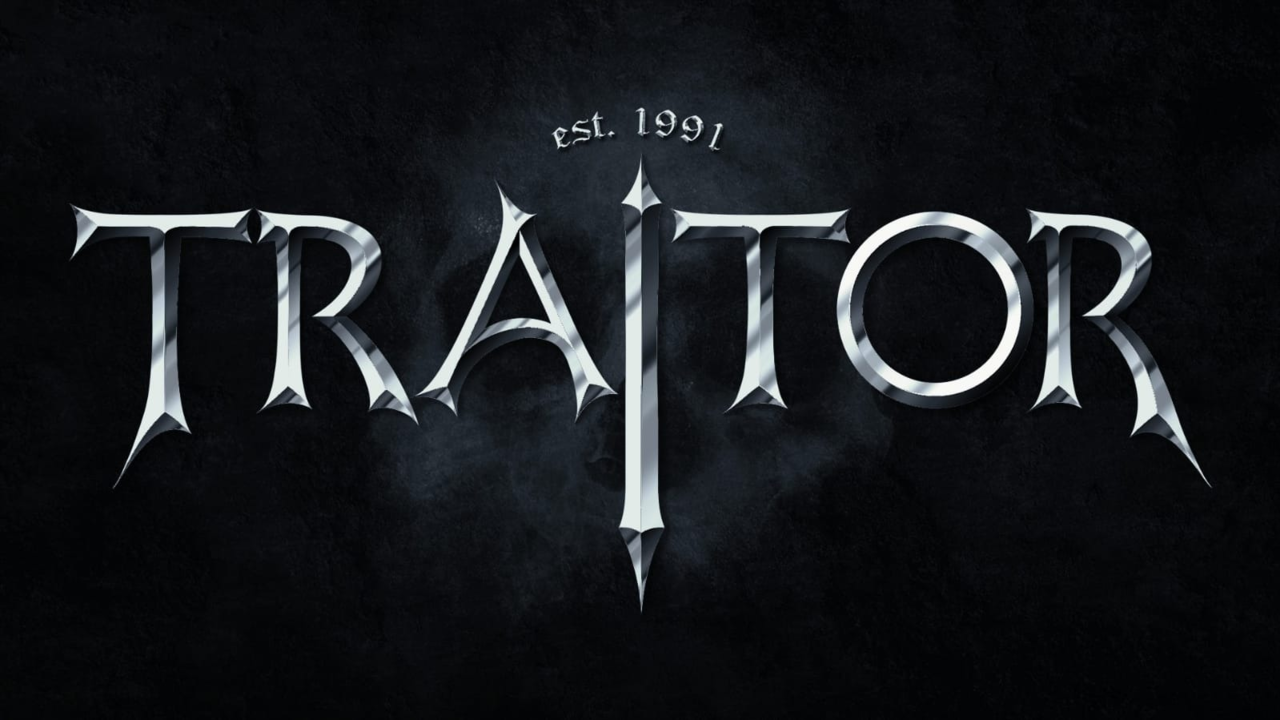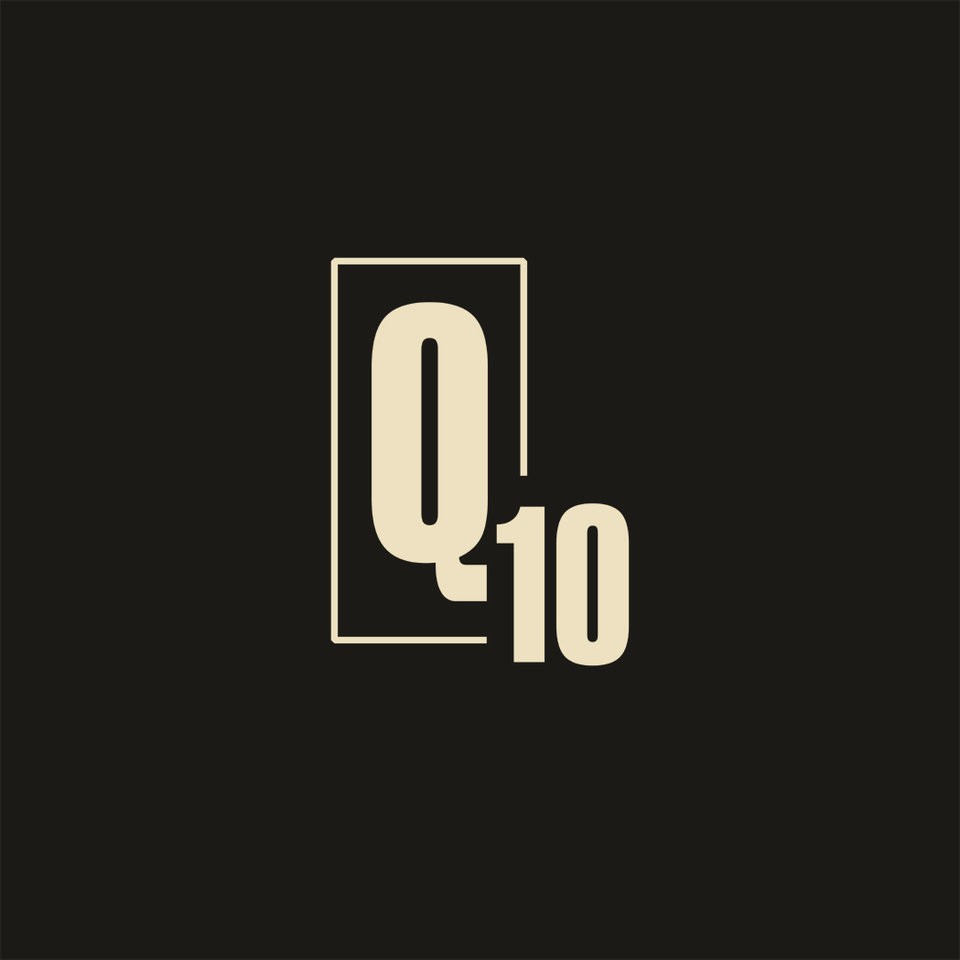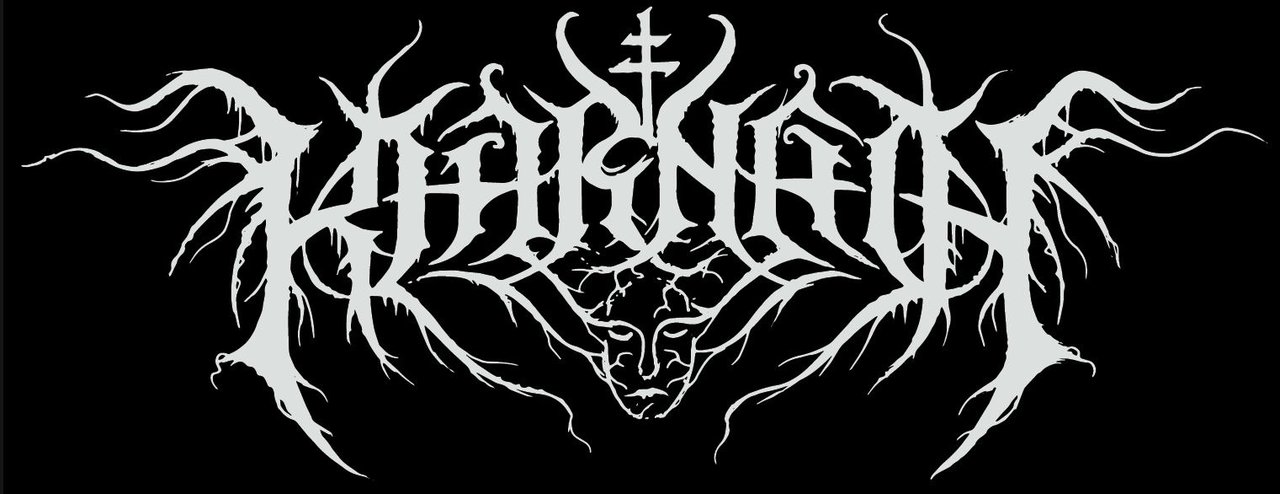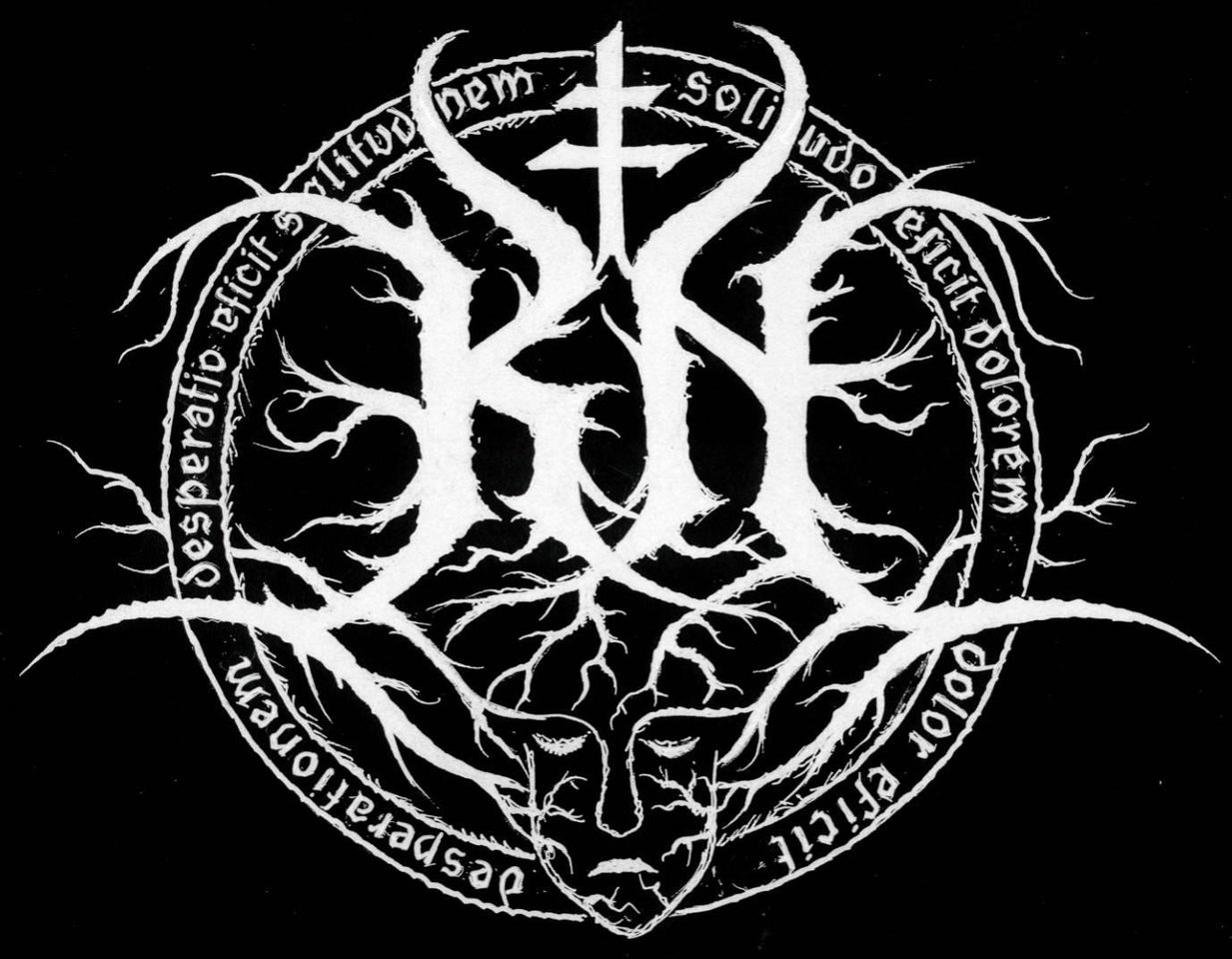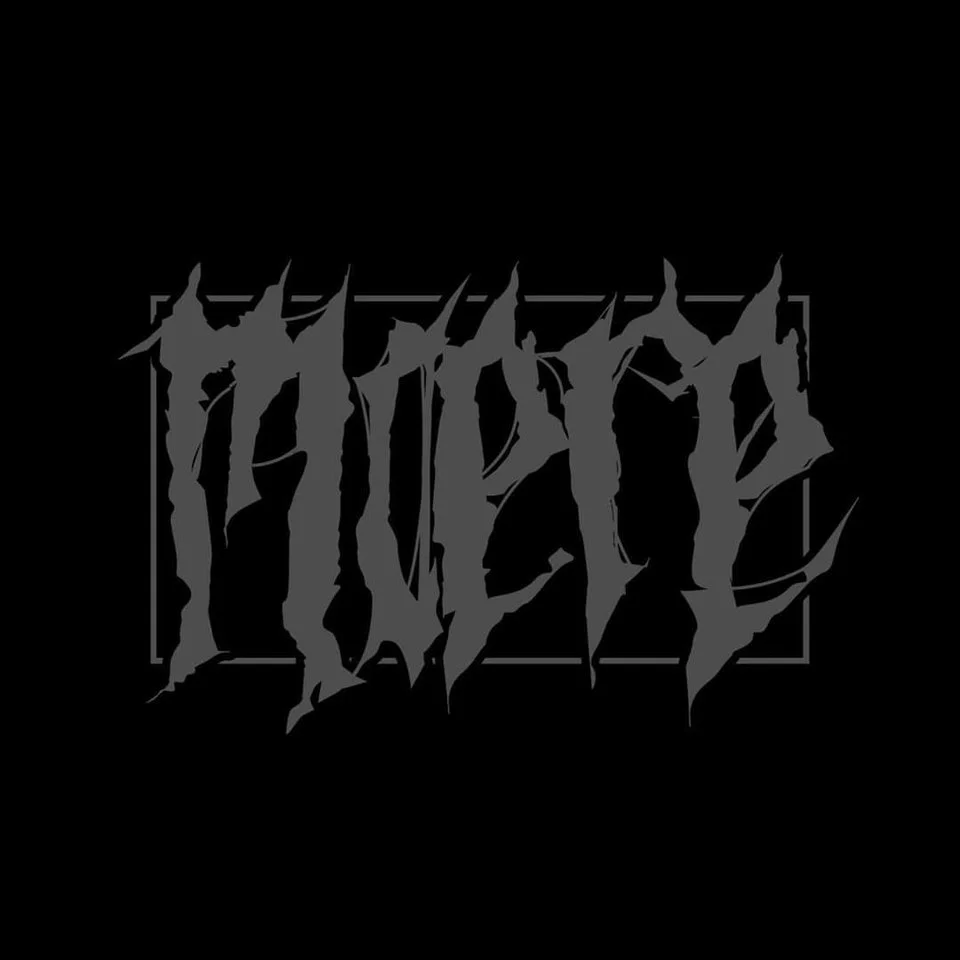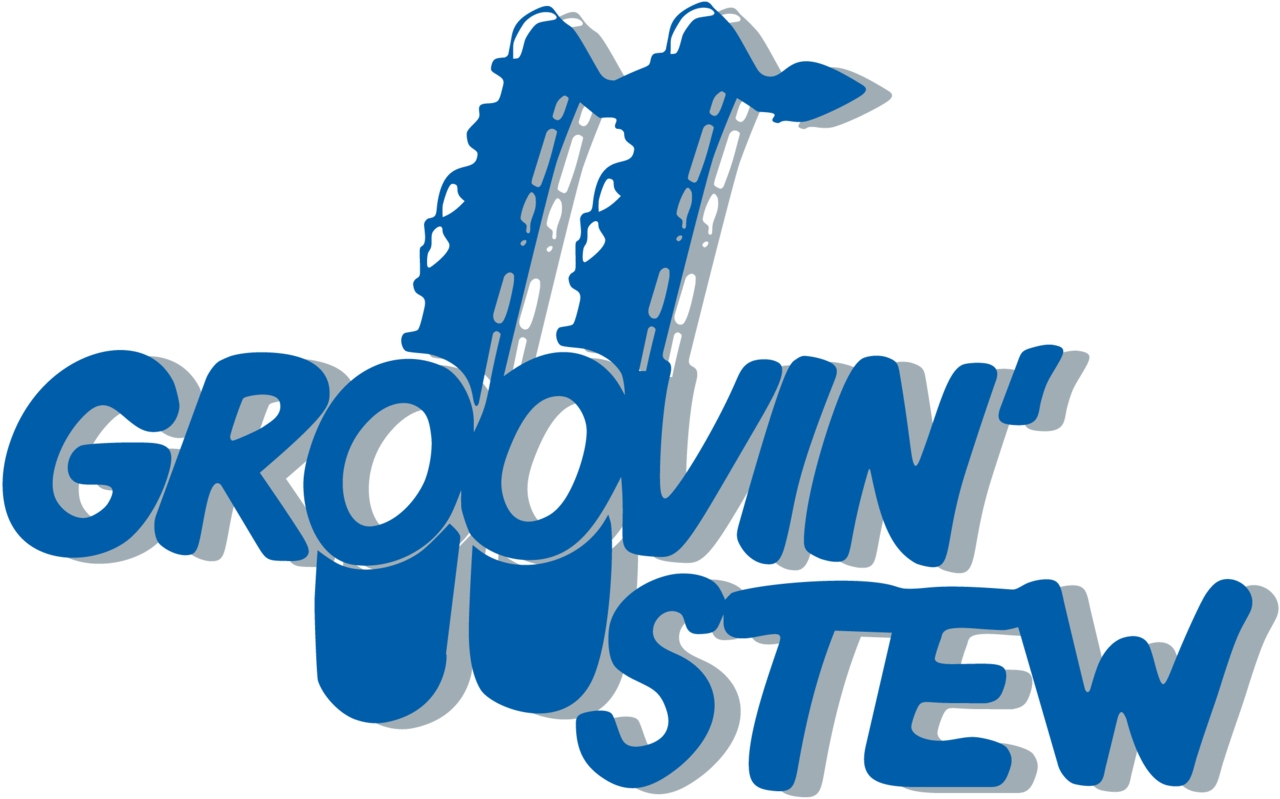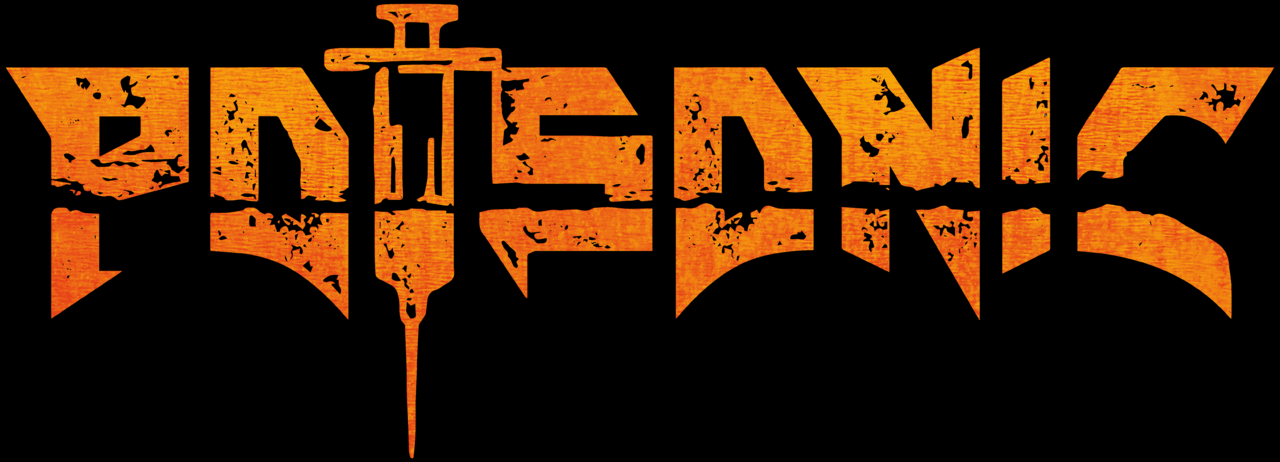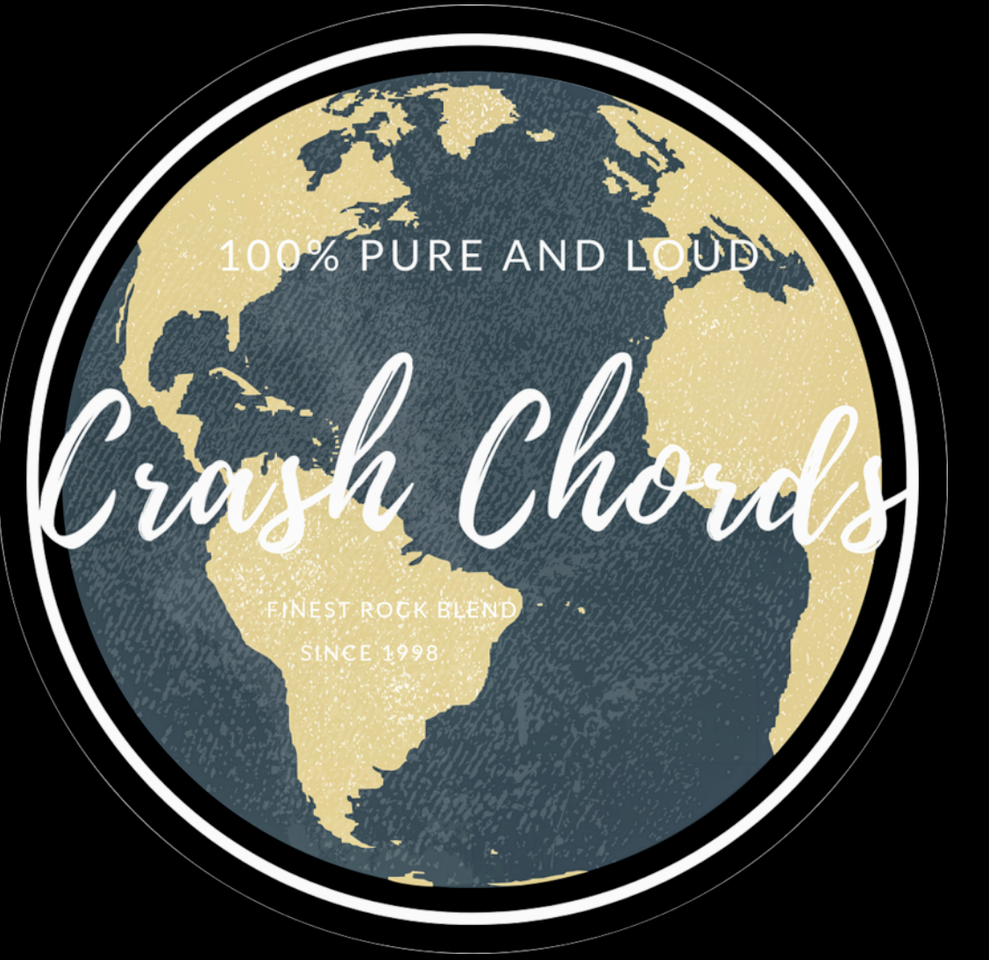
Euer Bandlogo-Artwork-Schriftart... her damit...!
Bei uns war der Name (Kharnath) eigentlich sofort gefunden, unseren Logodesigner (Christophe Szpajdel - unter anderem Verantortlich für Logos von Band wie Dark Fortress, Emperor, Moonspell, Nargaroth, Wolves In The Throneroom, Abigail Williams oder auch das aktuelle von Rhiana) haben wir einfach per Mail kontaktiert und angefragt und schon ging das ganze sehr flott und unkompliziert für das Logo und Bandsymbol von statten. Besonders gefallen hat uns dabei immer wieder, dass er Rücksprache mit uns gehalten hat und auch auf unsere Ideen udn Wünsche eingegegangen ist. Und natürlich dass der gute Herr noch alles per Hand zeichnet. UNd als Bonus ist er auch noch seeeeehr günstig gewesen, was uns aufgrund seines doch recht großen bekanntheitsgrades schwer verwundert hat. Und ein netter kerl noch dazu (schön zu sehen wie der Designer sich über ein Shirt mit seinem Logo freut, wenn man ihn zufällig auf nem Festival trifft).
Zu Herkunft des Namens und des Logos muß ich unseren Sänger in seiner Eigenschaft als einzig verbleibendes Gründungsmitglied befragen. Ich bin ja erst seit Anfang diesen Jahres dabei.
Edit möchte ergänzen, daß das auf schwarzem Hintergrund besser aussieht. In der Grafikdatei war der aber offenbar nicht mit drin...
Edit2: Interessanterweise hat man schwarzen Hintergrund, wenn man die Grafik anklickt. Kann man das beim Einbinden auch einstellen?
Der Hintergrund ist transparent, deshalb direkt im Thread so wie dargestellt. Das Plugin hier beim Anklicken hat standardmäßig den schwarzen Hintergrund, der dann logischerweise auch hinter der Transparenz gezeigt wird. Windoofs Bild-Anzeige interpretiert gefühlt je nach Laune Transparenz zu schwarz oder zu diesem Blassgrau ausm Explorer.
das hier is das logo meiner ex-band, gestaltet von einer befreundeten grafikerin. sehr schön schlicht, reduziert, finde ich bis heute super.
für die aktuelle band sind wir noch auf der suche nach einem schönen design. spätestens, wenn der mix der aufnahmen fertig ist, brauchen wir was für's tapecover ...
Mein Gehirnblitz in Krankheit bei Fall vom Dach. Alles fanden es gut und so war es geboren.
Steht ja in ähnlicher Art in vielen Straßen :rolleyes:
Tadaaa
Moere? Aber nein, das schreibt man ja mit "h". :gruebel:
Hier haste's orange auf schwarz als Bilddatei:
(Sieht ja auch wirklich besser aus.)
Zur Gestaltung:
Das ist auch Metall-Stil. Kann man aber gut lesen. :great:
Und überaus originell ist es auch noch.
Das ist das Logo von meinem Buntmetall-Projekt: